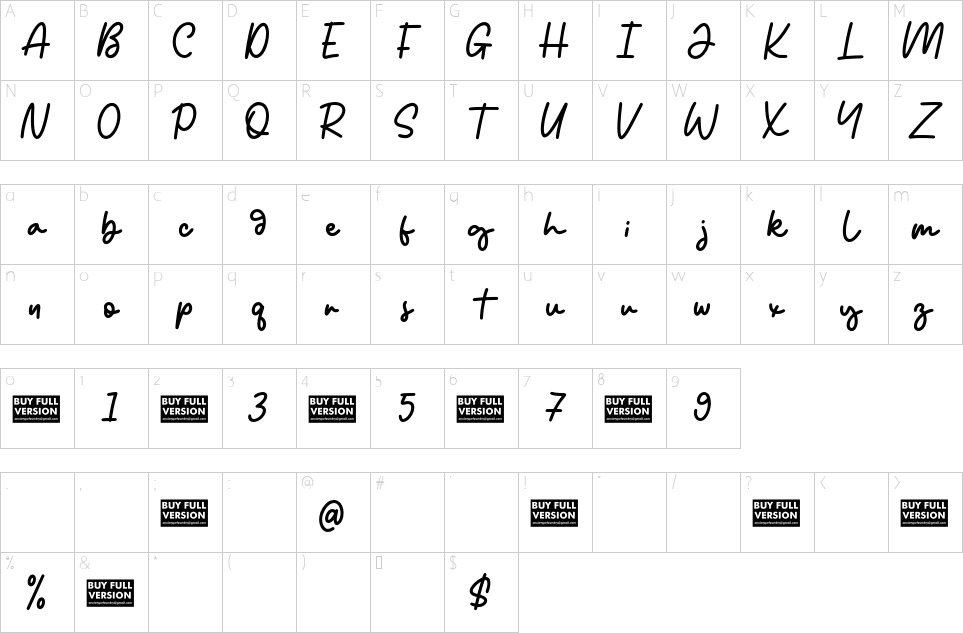
Reileight Winterlane Font – Download Grátis
Aqui está uma descrição envolvente para a página de download da fonte ‘Reileight Winterlane Font’, em português: ‘Parece que você encontrou a fonte perfeita para seu projeto: Reileight Winterlane! Desenvolvida pela Anxietype Foundry, essa elegante e moderna fonte garante um contraste impecável na sua criação gráfica. Para aqueles que apreciam uma paleta de cores suavemente clara e linhas finas, Reileight Winterlane é definitivamente para você. Com seu design cuidadosamente elaborado, a fonte traz um ar de sofisticação ao seu trabalho sem demandar muito esforço. Além disso, o designer não informado oferece a opção do download tanto para Windows quanto para Mac. Seja você um aspirante ou uma profissional, Reileight Winterlane é uma escolha perfeita para quem busca qualidade e simplicidade em cada caractere.’